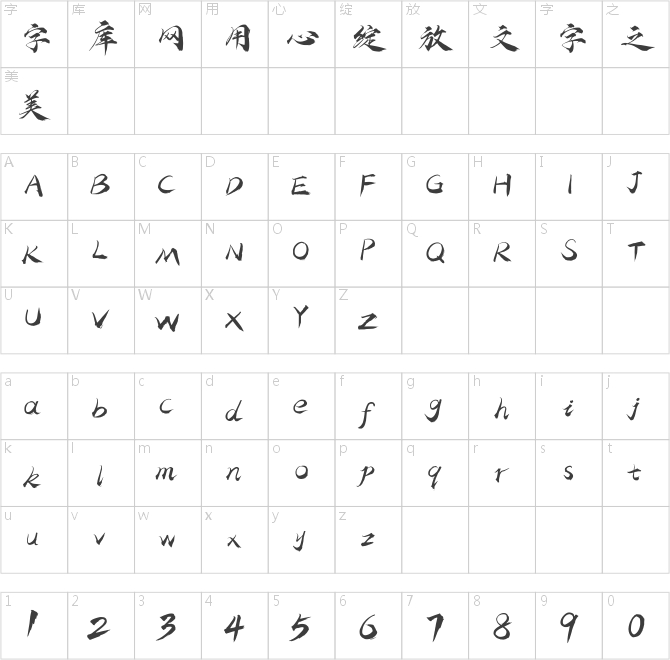
站酷鴻遠(yuǎn)御風(fēng)體
御風(fēng)體以行楷的體勢為基調(diào),區(qū)別于傳統(tǒng)的書法字體,更為注重線條的粗細(xì)變化從而豐富字形的節(jié)奏感使字體更具設(shè)計感,這款字體剛?cè)岵?jì),御風(fēng)而行的筆勢飄逸靈動,是一款具有現(xiàn)代感的個性化商業(yè)手寫字體,適合品牌標(biāo)志、招牌、包裝、海報、影視綜藝、廣告、游戲、漫畫等眾多場景應(yīng)用。